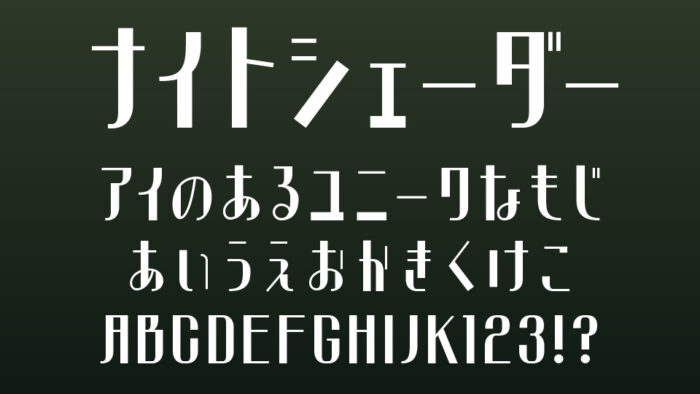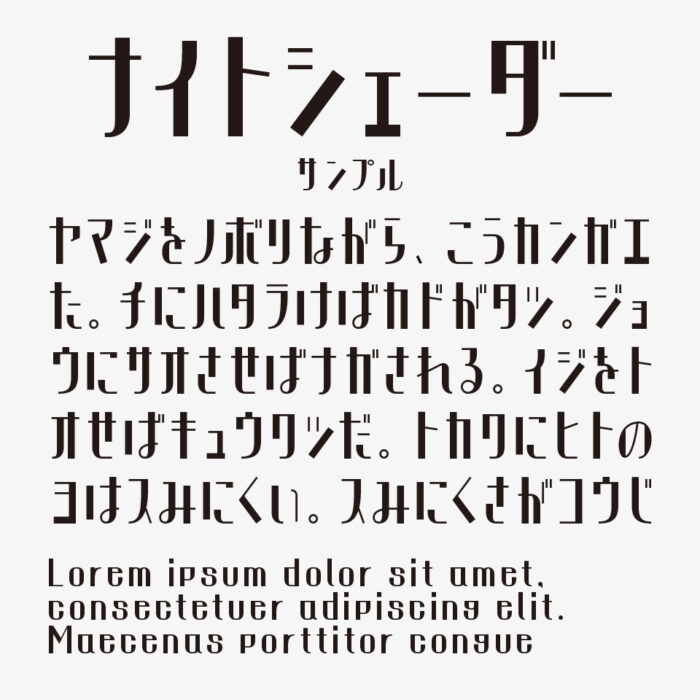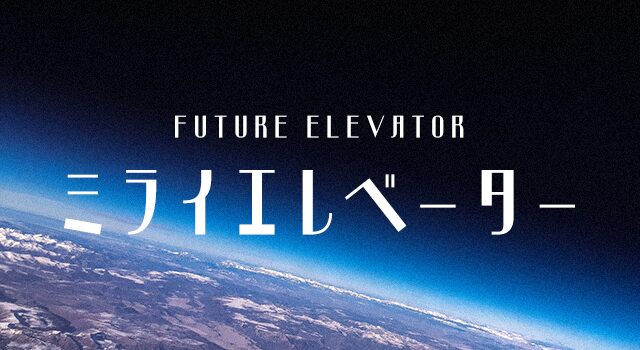
ナイトシェーダーフォントは、細身でシャープな骨格をもつモダンなデザインフォントです。
スラッとした直線的で、縦と横の線幅が異なることでが視覚的にリズムが生まれるよう工夫されておりとてもかっこいい仕上がりとなっているデザインです。近未来的なSFチックやサイバー感な印象があるスタリッシュなフォントです。
ロゴタイプのようにも使えるので、映像タイトルロゴや同人誌などにも活躍できるフォントです。
収録文字は、ひらがな・カタカナ・アルファベット・数字・記号が収録されています。